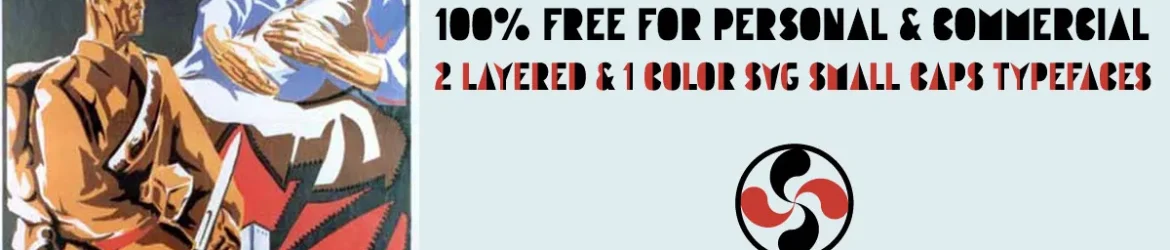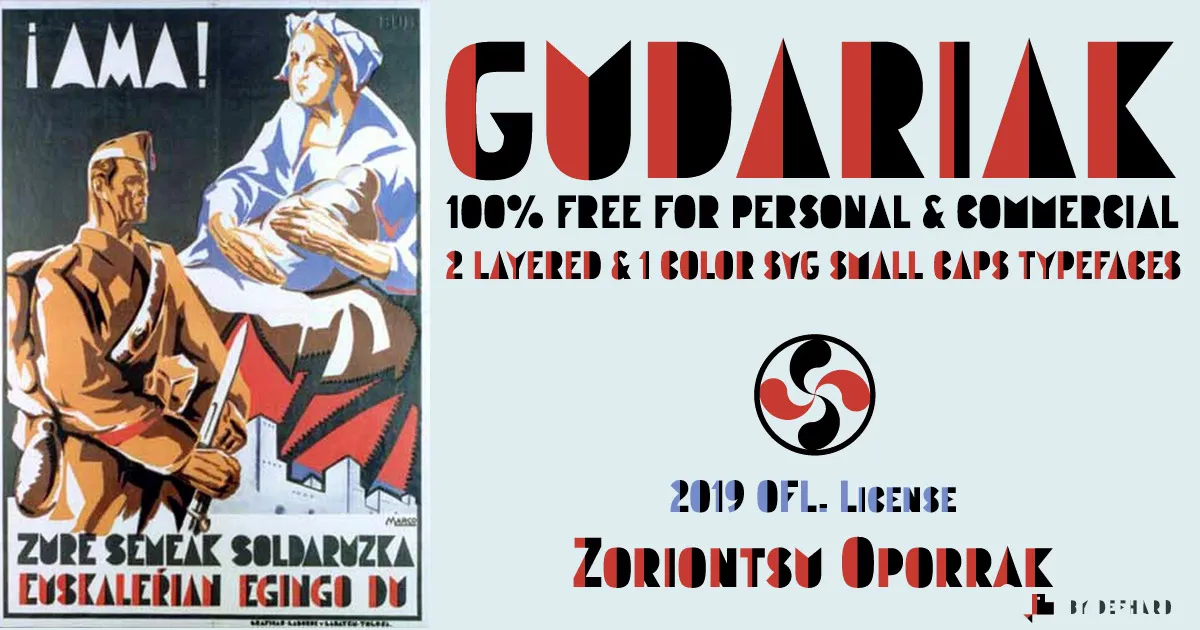
GUDARIAK Typeface – Fonte Grátis
GUDARIAK Typeface
A GUDARIAK Typeface é uma elegante escolha para designers que valorizam um estilo moderno com influências artísticas avançadas. Seu design original vem do trabalho do designer de gráficos e artista postal valenciano Vicente Ballester, que foi parte da CNT durante a Guerra Civil Espanhola. O trabalho de Ballester destaca-se pela sua clara influência modernista e post-cubista, característica presente em suas propagandas políticas criadas no contexto revolucionário da Espanha Contemporânea. A GUDARIAK Typeface reflete exatamente essas nuances, com linhas retas e formas orgânicas, proporcionando um equilíbrio entre modernidade e expressividade artística. Seu uso é ideal para criar mensagens visuais impactantes em design de arte ou comunicação visual, dando vida a qualquer projeto com seu estilo único que ressoa claramente com o movimento cultural da época.